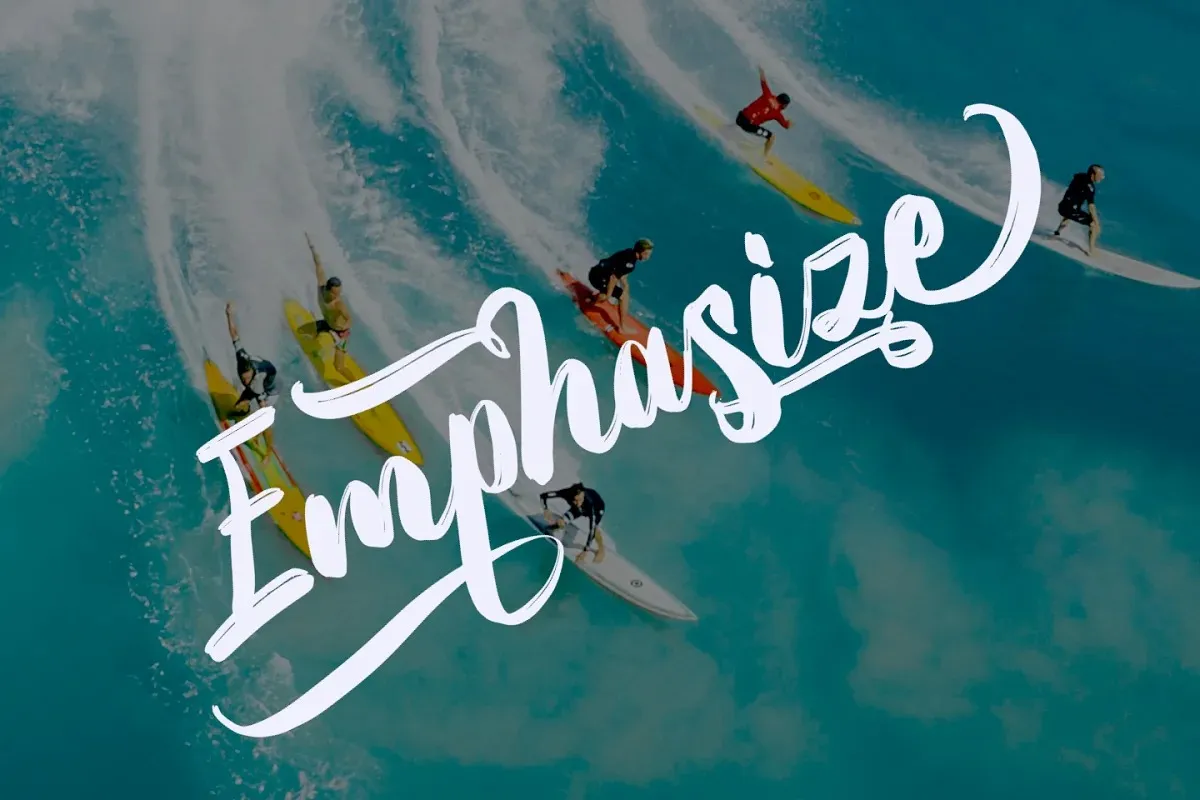
A Emphasize Font é uma elegante escolha para aqueles que valorizam a autenticidade dos traços escritos à mão. Desenvolvida como um script curioso e fluido, foi primeiro escrito de forma casual e rápida, posteriormente capturado através de leitura de imagens e cuidadosamente detalhado em formato vetorial. Esta fonte única e encantadora será perfeita para aqueles que desejam dar vida a seus projetos de design mais expressivos. Embora o designer 99designs tenha criado uma fonte com 454 caracteres gráficos e um vasto conjunto de códigos de 461, ela não se limita apenas aos textos. Com seu estilo fluido e atraente, esta font pode adicionar profundidade e originalidade a qualquer projeto design que você esteja trabalhando. Seja para anúncios em redes sociais, logotipos criativos ou até mesmo gráficos de marketing personalizados, a Emphasize Font é uma escolha inspiradora e única. Aproveite esta oportunidade para fazer sua marca se destacar com essa fonte única e versátil. Ela oferece um leque de 63 idiomas para adaptar a qualquer projeto em que você esteja trabalhando, proporcionando flexibilidade para designers de todo o mundo expressarem suas ideias de maneira distintiva.